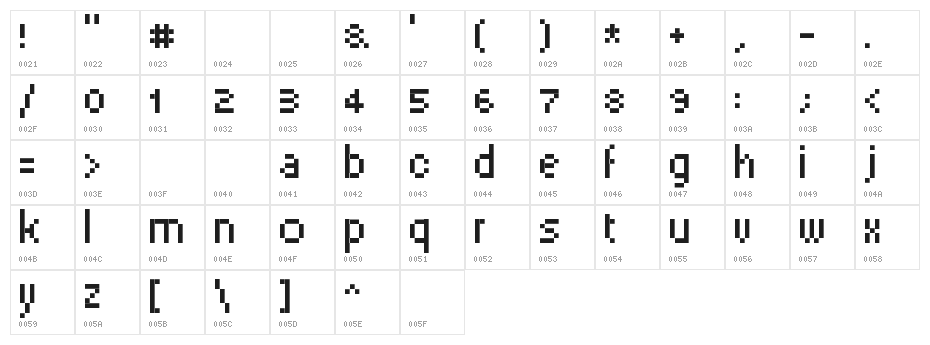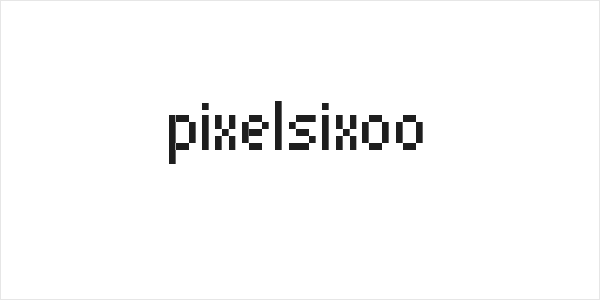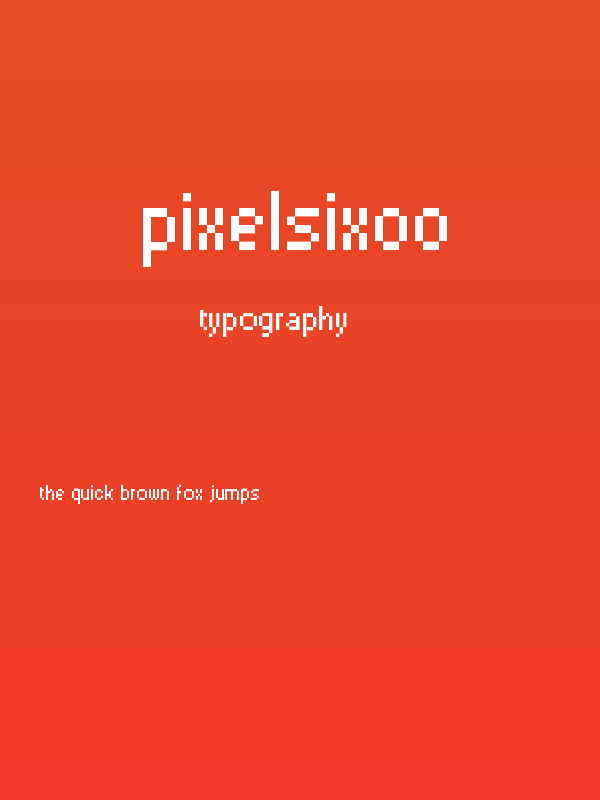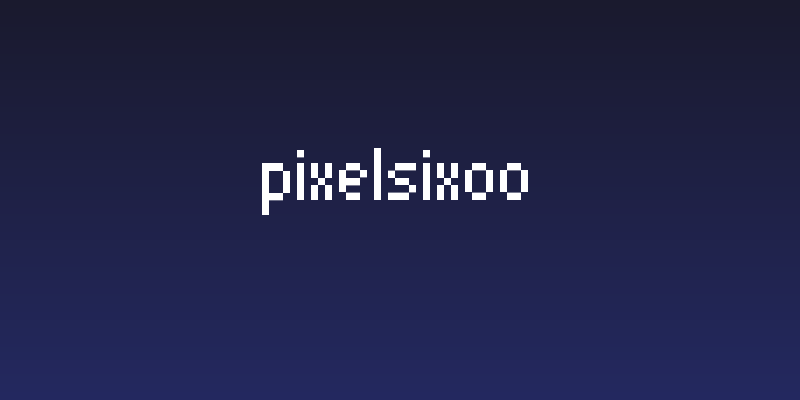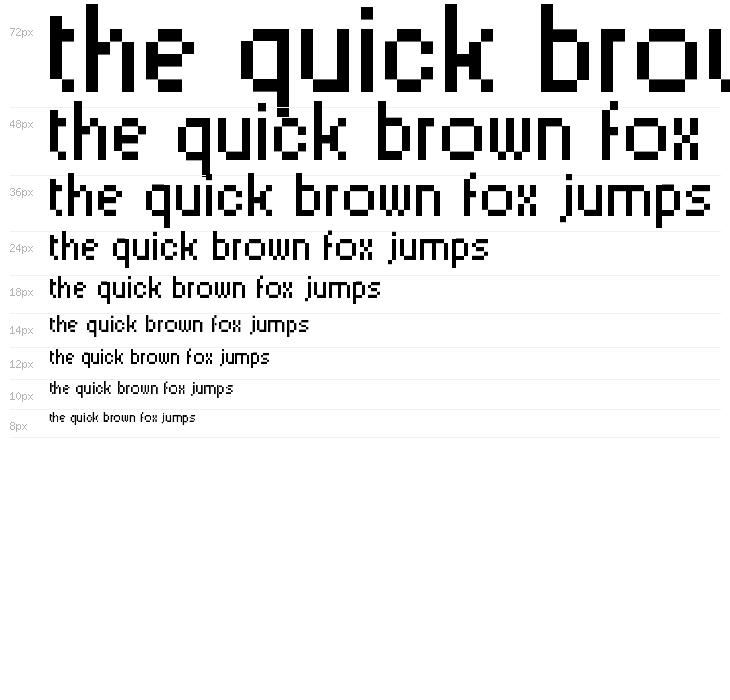
PixelSix00 Font
| Kategorien | Pixel |
| Gesamtstil | Vintage |
| Anwendungsfall | Logos, Digital displays, Video games |
| Vorgeschlagene Projekte | Ideal for retro video games, digital art projects, tech-themed designs, and nostalgic branding. |